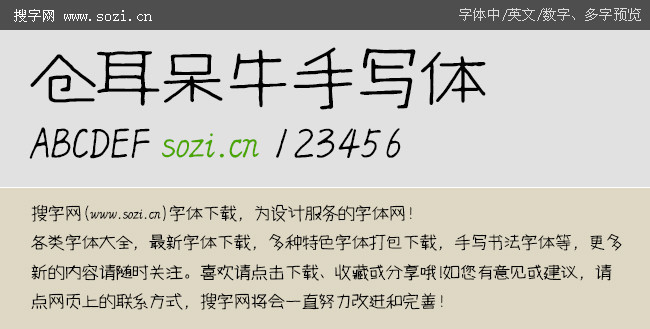
倉(cāng)耳呆牛手寫體
搜字網(wǎng)給大家提供一款倉(cāng)耳呆牛手寫體中文字體下載,倉(cāng)耳呆牛手寫體簡(jiǎn)單隨和,整體看起來(lái)非?蓯(ài)、清新。適合應(yīng)用于藝術(shù)設(shè)計(jì)、平面宣傳設(shè)計(jì)、網(wǎng)頁(yè)設(shè)計(jì)等應(yīng)用。(本字體為個(gè)人非商用版,如需要商用請(qǐng)聯(lián)系官方購(gòu)買版權(quán))